这是一款兼具现代感与传统韵味的哥特宋体,适合用于科技类品牌、潮流感产品的618宣传横幅与标题设计。笔画硬朗锐利,视觉冲击强烈,让你的促销语气场全开!
电商banner、手机数码类促销图、科技品牌主KV
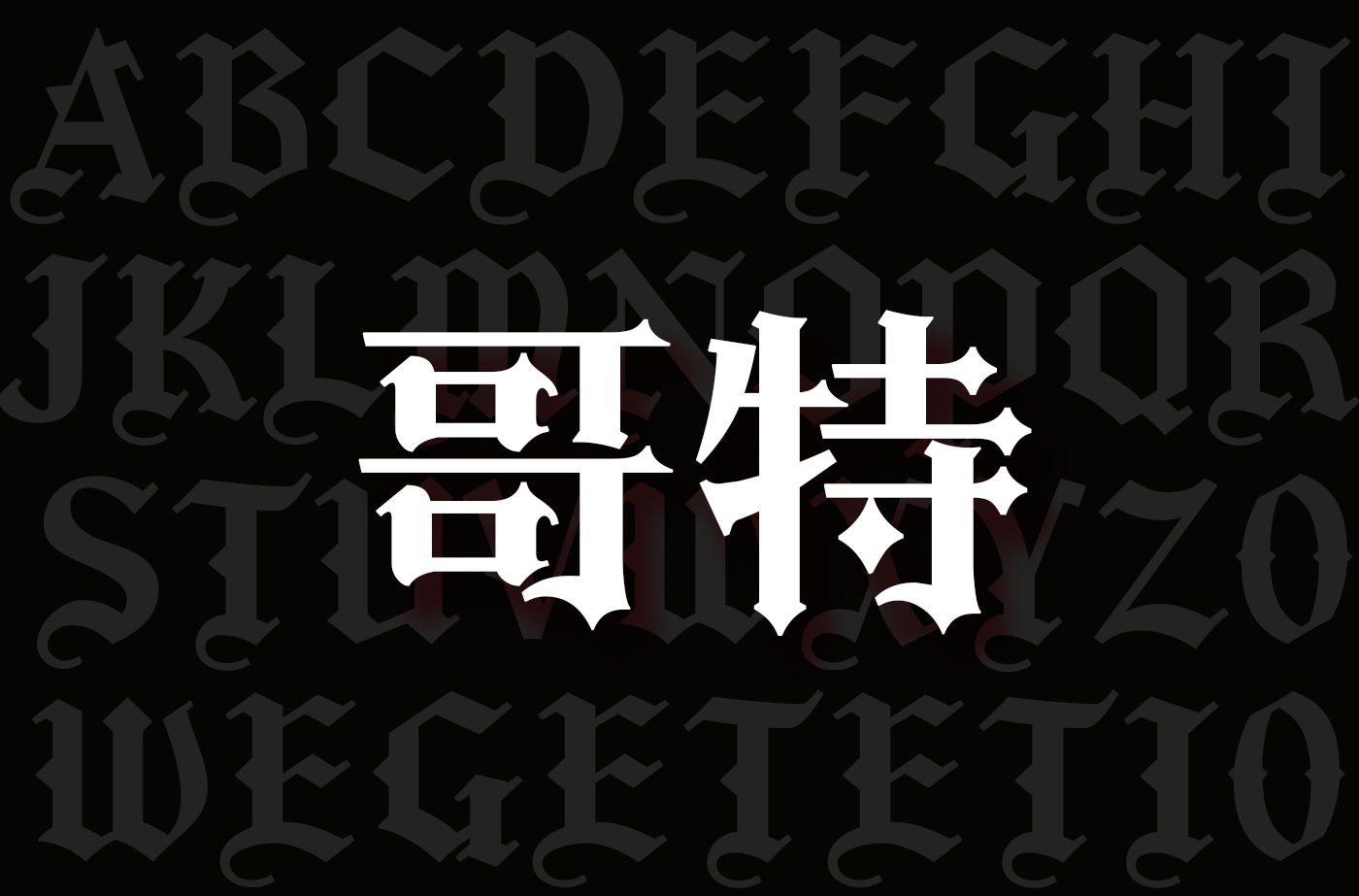
行楷之中透出书法韵味,又兼顾现代易读性。适合文创、美妆、生活方式品牌在618期间的温情文案与质感排版。让字体本身成为一种情绪传达。
短视频封面文案、文艺品牌海报、温情类文案主图
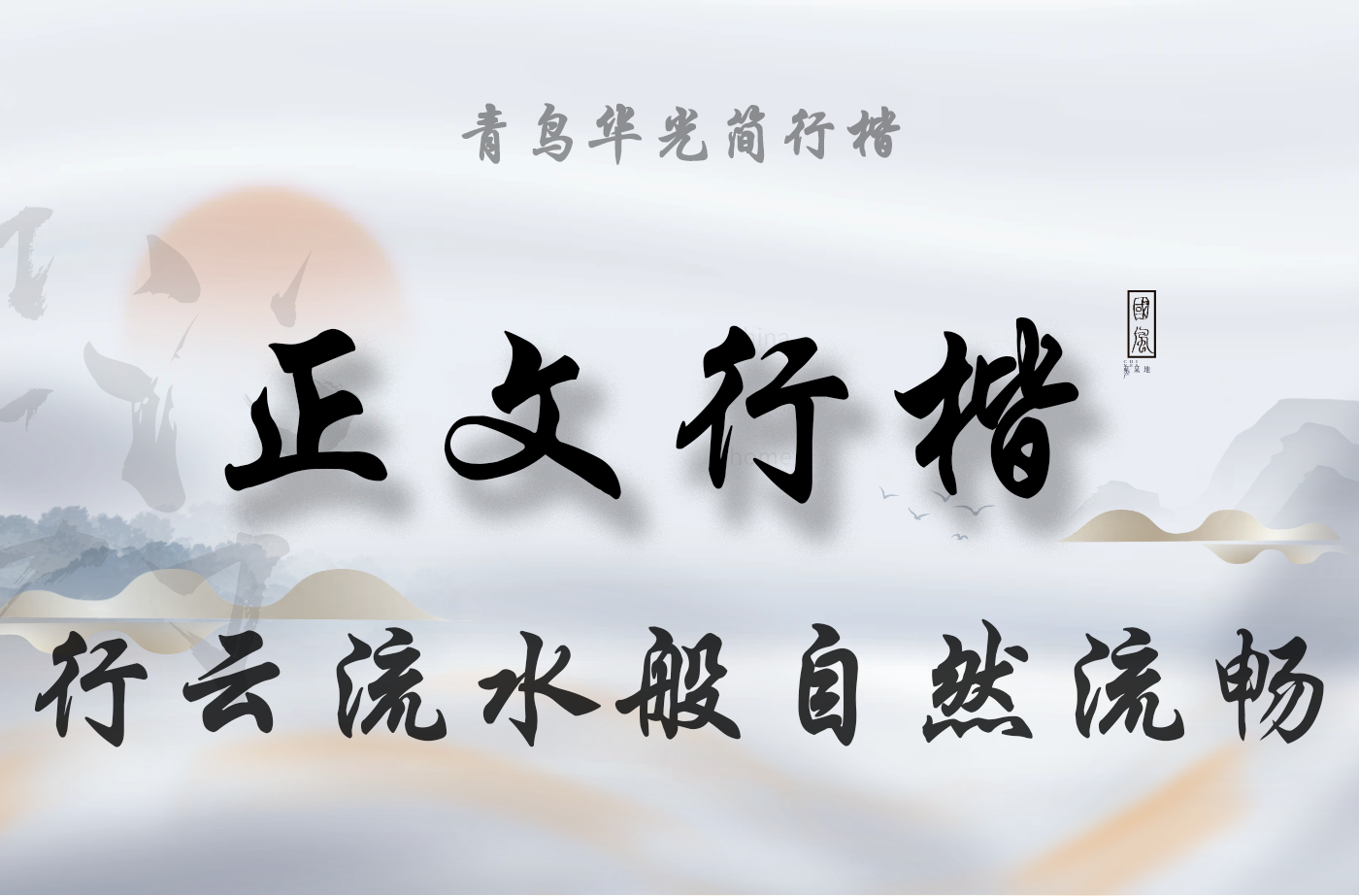
想要打造差异化的视觉效果?这款极具辨识度的小篆体无疑是一种个性选择。适合国风类品牌、文博类促销活动的主视觉搭配,彰显文化底蕴。
国风电商页、汉服促销KV、博物馆联名周边包装
这款手写体犹如漫画人物的独白,充满童趣与活力。适合母婴、儿童、玩具、美食类品牌,轻松营造出618的欢乐气氛。
萌系促销页、零食包装、互动海报、直播间文案
极具视觉冲击力的毛笔风格字体,粗犷中带着张力,极适合电商爆款主图、秒杀活动字眼等一切需要“抓眼球”的视觉点!
“秒杀”“疯抢”字眼、短视频强节奏字幕、电商红标活动图
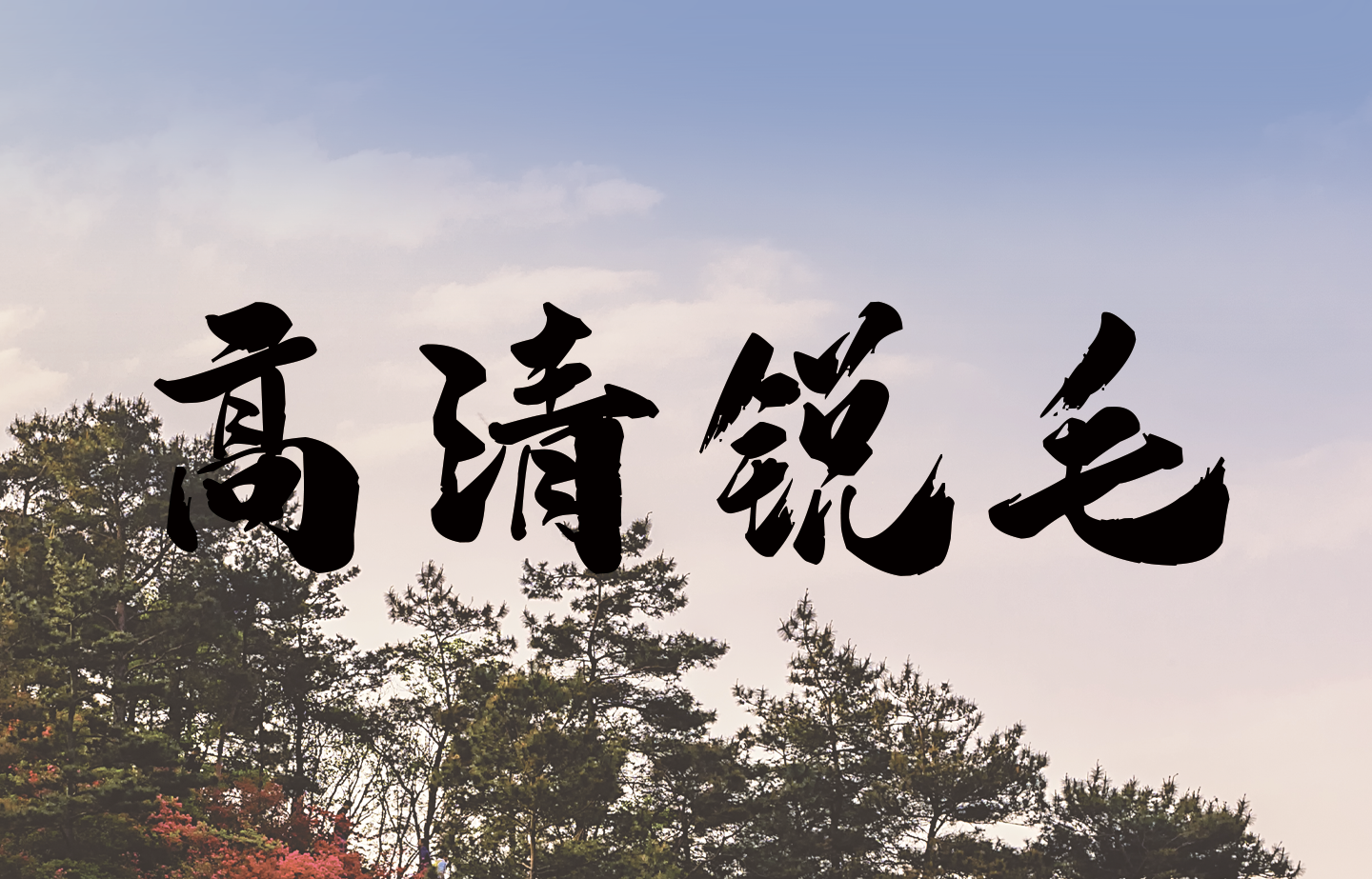
字体圆润饱满,仿佛软糖般Q弹可爱。适合甜美风格品牌,年轻化视觉定位的品牌推广,打造618独属的甜美视觉风格!
少女系品牌、零食、甜品、电商首页糖果色系设计